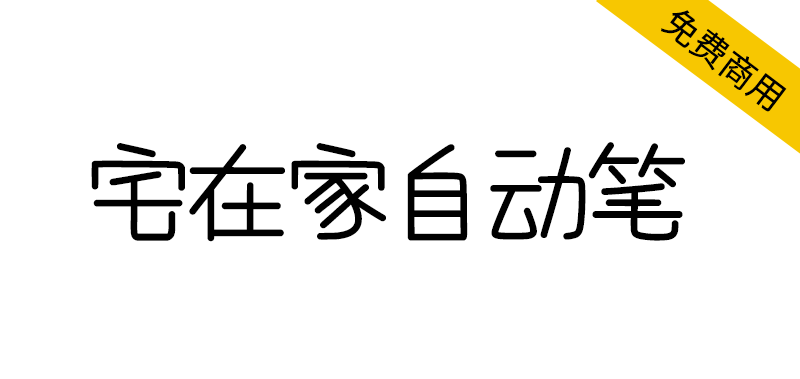
宅在家自动笔这款字体从2018年12月开始构想,于2019年7月完工,历时半年。第一次尝试制作字型,不是很好看。虽然中文字超级多,但是还挺有趣的。字体制作完成后,在记事本上试打,自己算是很满意。平常在纸上写字就是方方正正的风格,想试试看这种字体搬到电脑上用起来会是什么感觉。
我使用Medtbang Paint Pro绘图软件,手抖修正设定为35,手绘板是Viewontc的WoodPad,字型编辑软件使用免费开源的FontForge制作。